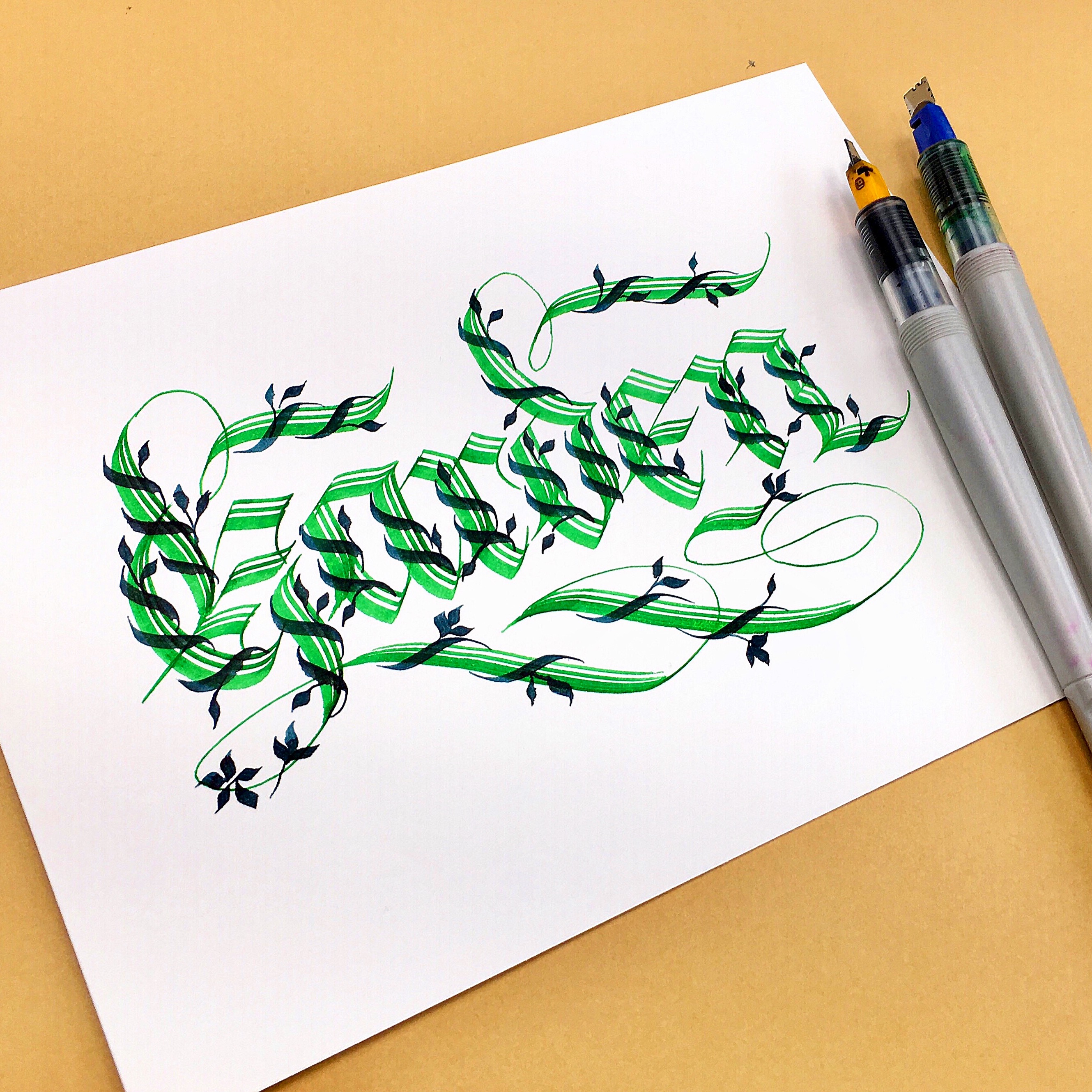
【 哥德體 】Garden 藤蔓 字體 🌿 Posted on 2022-05-262022-05-26 by Charling 水占文房 改分叉尖 6.0mm 平行筆,寫出來的字體效果有點像”樹幹“的紋路,用2.4mm的筆尖,繞著字體加上曲線與葉子,就是很有趣的 藤蔓 字體囉! 🥰喜歡平尖 #哥德字體 的朋友,也可以參考我開的 { 哥德字體線上課程👉 http://bit.ly/2CoU7r1 },從基礎練習學起,到字體的群組結構練習,即可輕鬆學會手寫哥德字體喔! 筆具:百樂平行筆 分享此文:更多Tweet在 Tumblr 上分享 分享到 WhatsApp(在新視窗中開啟) WhatsApp